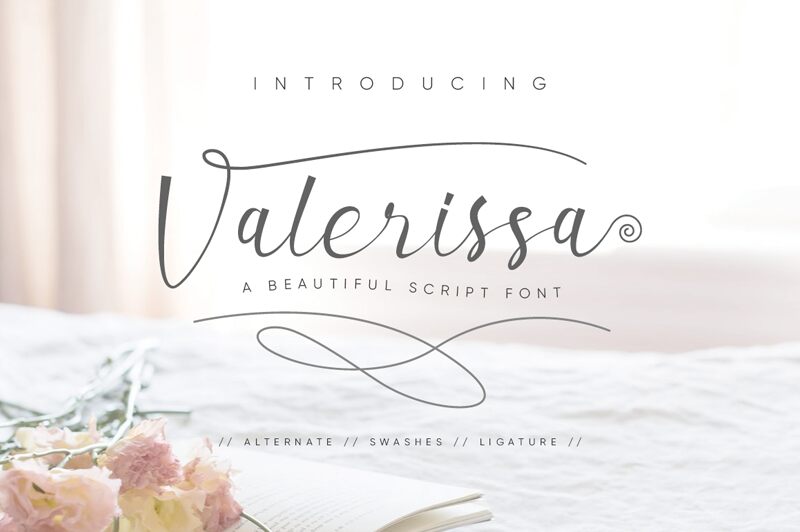
Valerissa, creata dal talentuoso Jani Nurman, è un font calligrafico che trasuda eleganza e raffinatezza. Con il suo peso semi-leggero, Valerissa trova un equilibrio delicato, offrendo finezza senza sacrificare la leggibilità. Le curve artistiche e le linee fluide caratteristiche di questo stile riflettono una visione contemporanea della calligrafia tradizionale, rendendola una scelta versatile per svariati progetti di design.
Il fascino estetico di Valerissa risiede nelle sue proporzioni armoniose e nella grazia naturale con cui ogni lettera confluisce nella successiva. Il suo carattere moderno si adatta perfettamente a inviti, materiali di branding e packaging di prodotti di alta gamma in cui è richiesto un tocco di personalizzazione. Lo stile sfumato di questo font può valorizzare qualsiasi progetto creativo aggiungendo un senso di artigianalità su misura che si distingue nell'era digitale. Che vogliate infondere fascino al vostro lavoro o creare un'atmosfera accogliente attraverso la tipografia, Valerissa offre infinite possibilità ai designer che mirano a lasciare un impatto memorabile.